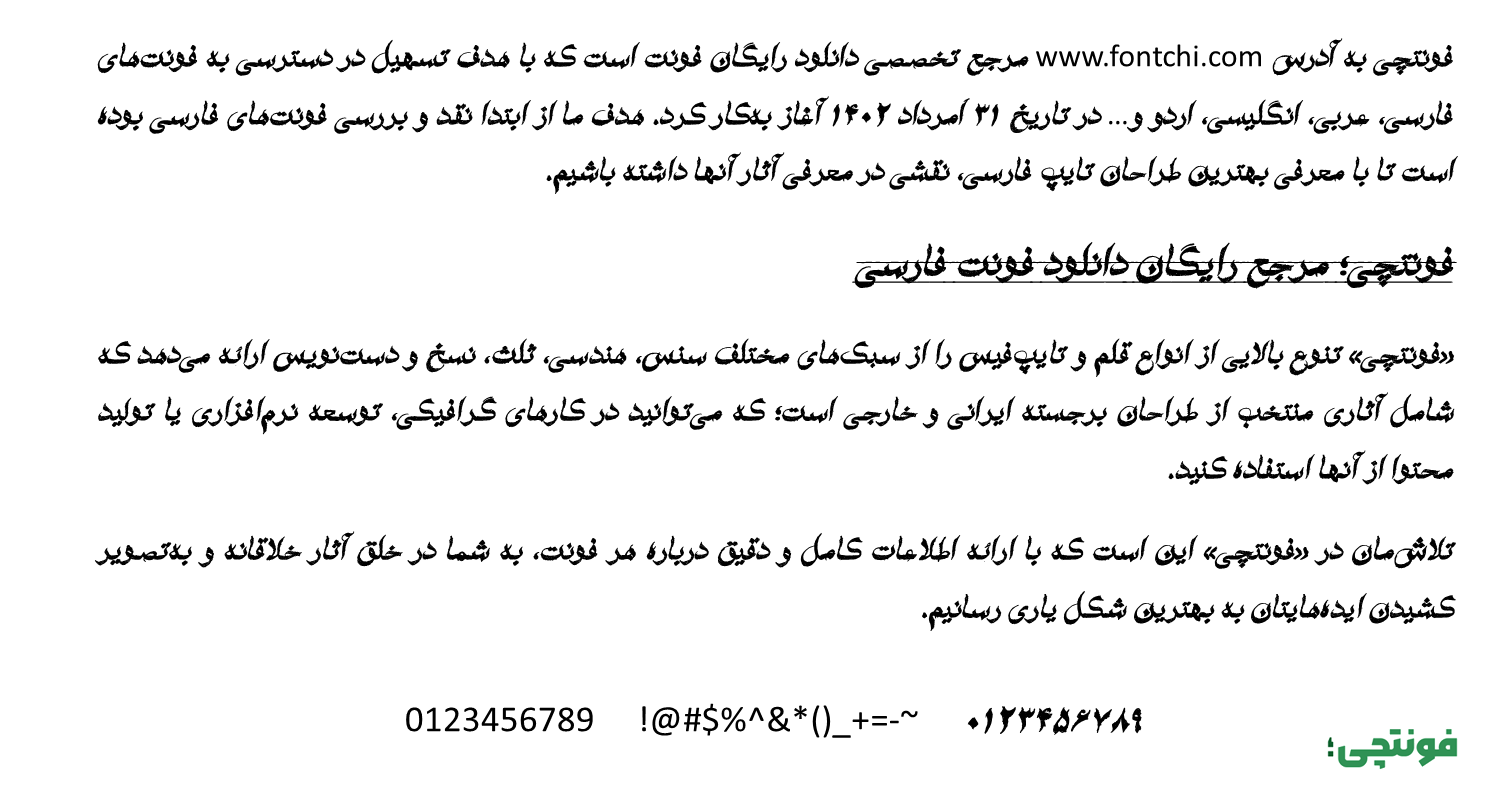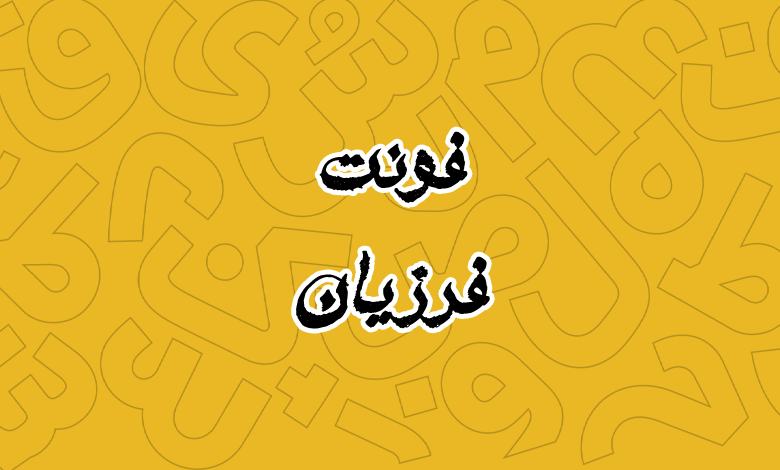
فونت فرزیان (Farzian)
فونت فرزیان (به انگلیسی: Farzian) قلمی با طراحی فانتزی و گرافیکی است که میتوانید از آن در پروژههایی که ساختاری فانتزی و نمایشی دارند استفاده کنید. این فونت با ترکیبی از سبک سنتی و مدرنیته خلق شده است که ظاهری صمیمی ایجاد میکند.
فونت فرزیان توسط سید روحالله میرمحمدی طراحی شده است. دو نسخه از این فونت در دسترس است که شامل نسخه معمولی و نسخه خطی است. در تصویر زیر تصویری از پیشنمایش این فونت را میبینید.
فونت فرزیان با الهام از سبکهای سنتی و مدرن، توانسته جایگاهی ویژه در میان فونتهای فارسی پیدا کند. فرزیان در دو نسخهی خطدار و بدون خط ارائه شده است که این تنوع، کاربرد آن را گستردهتر میکند. فونتی فانتزی و دستنویس که حس و حال سنتی را با ظرافتهای مدرن ترکیب کرده است.
فرزیان برای متون کوتاه، عناوین، پوسترها، لوگوتایپها، کارتهای ویزیت و محتوای اینستاگرامی بسیار مناسب است. این فونت بهویژه در طراحیهای مرتبط با مضامین تاریخی، فلسفی، ادبی و دینی جلوهی خاصی دارد. با این حال، برای متون بلند و پیوسته (مثل کتاب یا مقاله) به دلیل سبک تزئینیاش چندان توصیه نمیشود.
این فونت رایگان بهطور کامل از حروف فارسی و عربی پشتیبانی میکند و برای زبانهایی مثل کردی نیز کاربرد دارد. برای زبانهای لاتین، نیاز به ترکیب با فونتهای مکمل دارید. وزن پشتیبانی در این فونت عبارت است از:
خوانایی فونت فرزیان در اندازههای بزرگ، عناوین یا متون کوتاه بسیار خوب است. طراحی حروف بهگونهای است که توجه مخاطب را به سرعت جلب میکند. با این حال، در اندازههای کوچک یا متون فشرده، ممکن است خوانایی کاهش یابد و نیاز به تنظیمات دستی باشد.